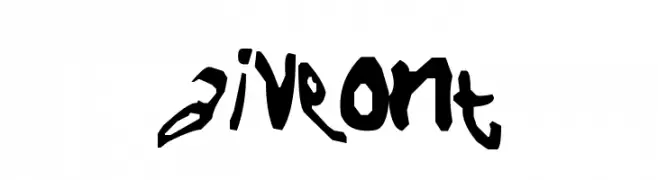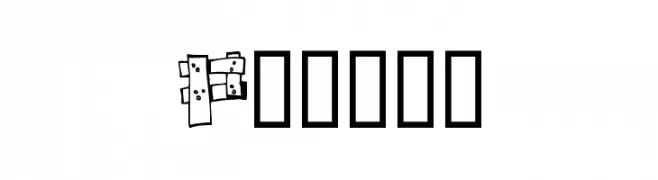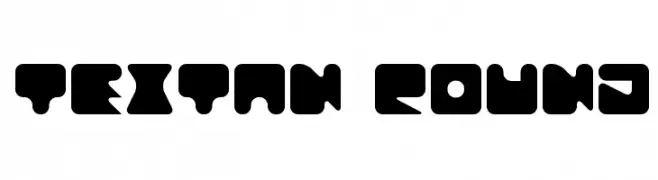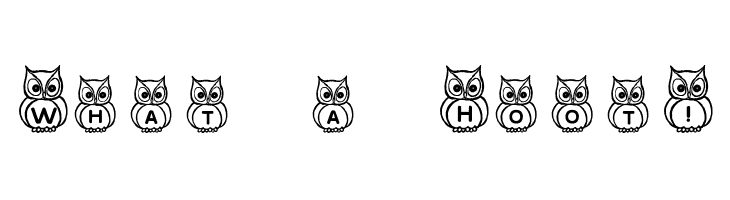
A futuristic, geometric font with bold, rounded characters and a modern appeal.
A bold, futuristic font with a leftward slant and angular design.
( Fonts by Omega Font Labs )
A bold, decorative font with rune-like characters enclosed in rounded shapes.
( Fonts by Mr Fisk - Mike Larsson - fontorama.net )
A whimsical and irregular hand-drawn font with a playful and artistic style.
( Fonts by Dieter Steffmann )
A classic blackletter font with intricate, ornate letterforms and decorative elements.
( Fonts by ShyFonts )
A bold, condensed font with high contrast and a modern, impactful style.
A bold, rounded, and playful font with a modern aesthetic.
现在大家都在用哪些新字体?
流行变化很快,但极简无衬线与个性鲜明的展示体当前更受欢迎, 特别适合移动端内容与现代品牌风格。
有哪些值得尝试的 5 款新字体?
近期热门包括 Planet NS, Grey[Alien]SW, 32 pages, Gunship Leftalic and Runez of Omega 它们在清晰度与个性之间取得平衡,适用于科技品牌、编辑排版与社媒视觉。